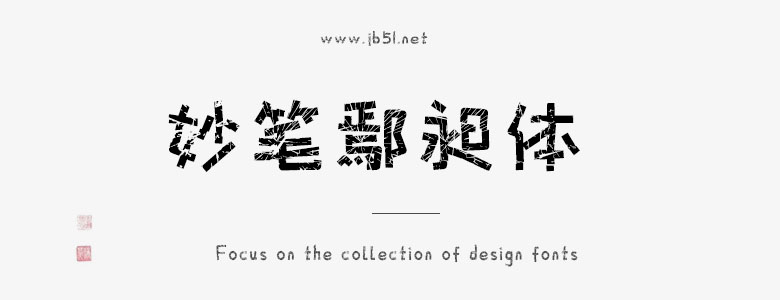
妙筆鄢昶體字體是由字魂字庫推出的卡通可愛字體,這款該字體包含6763個中文、字母、 符號和數(shù)字,具有簡約的風(fēng)格,適合應(yīng)用于藝術(shù)設(shè)計、平面宣傳設(shè)計、網(wǎng)頁設(shè)計,書法字帖等領(lǐng)域。
妙筆鄢昶體字體是一款商用的卡通可愛,英文無襯線體字體,該字體包含6763個中文、字母、 符號和數(shù)字,具有簡約的風(fēng)格,可以滿足您設(shè)計上的各種需求,該字體主要用于黨政公務(wù)等場景, 您不但可以在字魂網(wǎng)下載妙筆鄢昶體字體,同時還有眾多毛筆書法字體、創(chuàng)意字體等可供選擇!